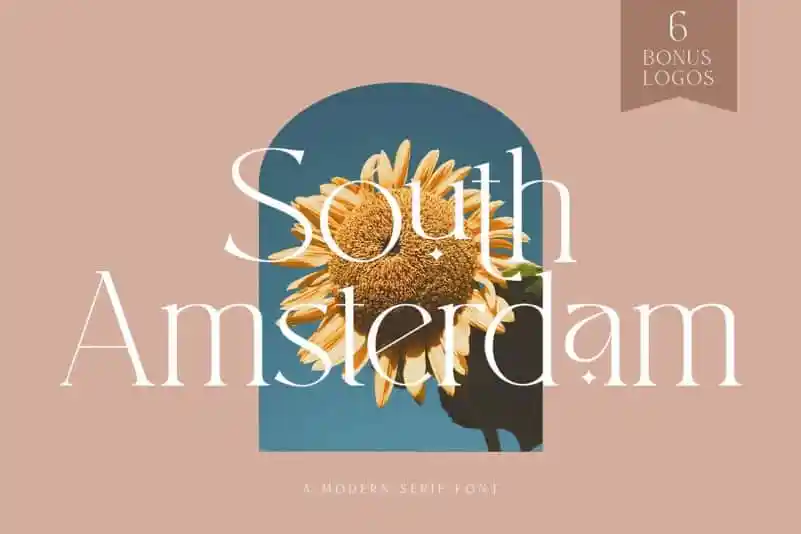
A South Amsterdam Serif é uma fonte serifa que combina a modernidade urbana da cidade holandesa com um estilo de escrita manual atualizada. Este tipo de letra é ideal tanto para uso expositivo quanto para aplicativos cotidianos, graças à sua legibilidade perfeita e versatilidade. A inspiração holandesa em cores vivas e edginess contrasta com o charme serifa tradicional que a torna adequada para um amplo espectro de usos. Com seus logotipos prontos, logos vectoriais e aplicações mais elaboradas como revistas, selos, embalagens de produto e design gráfico, a South Amsterdam Serif é perfeita tanto para designers profissionais quanto para iniciantes que buscam uma fonte moderna e atrativa.